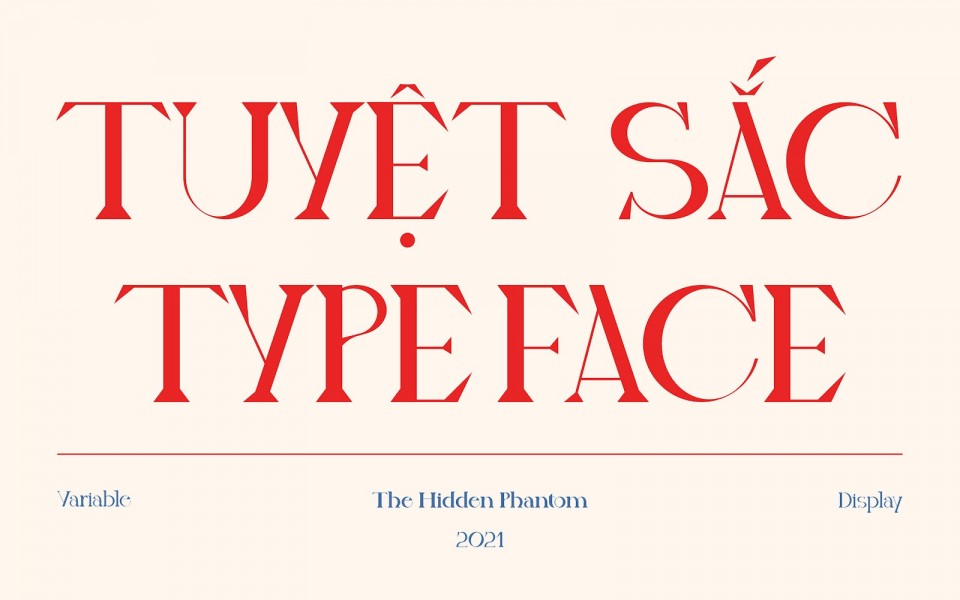
Giới thiệu về bộ Font tiếng việt Tuyệt Sắc
Trong thế giới đồ họa hiện đại, việc tìm kiếm một bộ Font Chữ phù hợp để truyền tải cảm xúc là điều vô cùng quan trọng đối với các bạn học sinh và thầy cô giáo. Font tiếng việt Tuyệt Sắc nổi lên như một lựa chọn hàng đầu nhờ phong cách thanh thoát, mang đậm nét nghệ thuật uyển chuyển. Đây là bộ font được tối ưu hóa hoàn toàn cho bảng mã Unicode, giúp người dùng dễ dàng soạn thảo các văn bản tiếng Việt mà không lo gặp lỗi hiển thị hay mất nét. Với thiết kế tinh tế, bộ font này giúp mọi bài thuyết trình hay thiệp chúc mừng trở nên sinh động và chuyên nghiệp hơn bao giờ hết.
Đặc điểm nổi bật của Font tiếng việt Tuyệt Sắc
Thiết kế mềm mại và linh hoạt
Điểm mạnh nhất của Font tiếng việt Tuyệt Sắc chính là những đường cong nét thanh nét đậm được trau chuốt tỉ mỉ. Bộ chữ này cực kỳ phù hợp cho các chủ đề về văn học, nghệ thuật hoặc các dự án sáng tạo trong nhà trường. Sự linh hoạt của nó cho phép ứng dụng từ tiêu đề báo tường đến các ấn phẩm truyền thông học đường.
Cách ứng dụng Font tiếng việt Tuyệt Sắc hiệu quả
Để khai thác tối đa vẻ đẹp của Font tiếng việt Tuyệt Sắc, bạn nên kết hợp nó với các màu sắc nhẹ nhàng hoặc tông màu pastel. Việc sử dụng đúng kích thước và khoảng cách dòng sẽ giúp nội dung trở nên thanh lịch, dễ đọc và thu hút ánh nhìn hơn. Đây chính là giải pháp hoàn hảo để nâng tầm giá trị cho các dự án cá nhân.